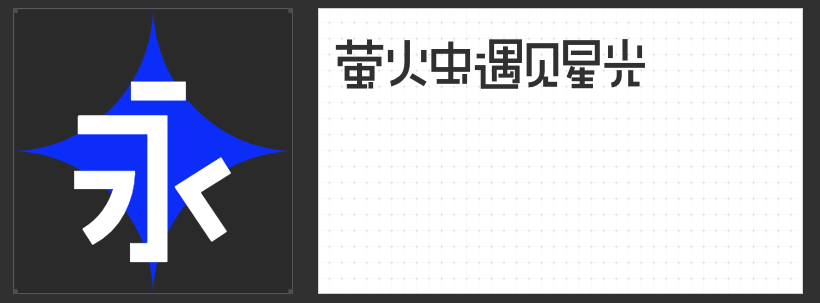
萌系设计字体推荐:用灵动字型唤醒治愈美学
在萌系设计中,字体的选择往往决定了整体氛围的基调——柔和的弧线、灵动的结构、恰到好处的“不完美”,都能让文字成为传递温暖与趣味的视觉符号。以下四款字体以独特的设计语言,为萌系创作注入鲜活的生命力。
一、励字敲可爱简 中粗
这款字体以手写圆润线条为基底,通过省略部分笔画与简化结构,打造出“用心书写却略带随性”的视觉效果。中粗的笔画粗细平衡了辨识度与轻盈感,避免因过于纤细而失去存在感,也未因过粗而显得笨拙。其独特之处在于保留手写痕迹的同时,融入几何化的处理——例如“口”字常被简化为圆角矩形,转折处带有自然的弧度,仿佛孩童信手涂鸦。这种“不完美的精致”让文字自带故事感,适合需要传递温暖、治愈氛围的场景。
二、字恋狂澄空 迟风
以“上松下紧”的重心布局为特点,这款字体通过灵活的字面结构与错落有致的笔画安排,营造出动态的视觉韵律。部分偏旁部首的占比差异(如左窄右宽或上小下大)打破常规平衡,却因整体协调的设计显得自然有趣。笔画处理上,流畅的弧线与利落的直线交织,折笔处采用平直切角减少锐度,搭配“断开”的笔画连接方式,让文字如音符般轻盈跳跃。这种设计既保留了手写的自然感,又通过结构变化赋予文字“呼吸感”。
三、字恋狂灵怪简
若说前两款字体是“温柔的萌”,这款则以“鬼马精灵”的气质脱颖而出。笔画连带处如行云流水,折笔处被刻意设计为三角形、圆形等几何图形,形成强烈的视觉记忆点。连笔的贯穿不仅提升了书写流畅感,更让文字仿佛拥有生命,在纸上自由舞动。这种打破常规的设计语言,适合需要突出个性、传递奇思妙想的萌系创作。
四、励字圆梦简 中黑
以圆润柔和为外衣,这款字体通过“外圆内方”的结构传递内在力量。直线笔画与竖折设计替代了传统弧线,简洁中透着利落;起笔、收笔与转折处的圆弧处理,则弱化了直线的生硬感。中宫松散的设计让文字如棉花糖般蓬松可爱,却因内方骨架而保持了结构稳定性。这种“柔软与坚韧并存”的特质,让文字既能营造温馨氛围,又不失专业感。
萌系设计的核心在于“情感共鸣”,而这四款字体通过手写温度、动态结构、几何创意与刚柔并济的设计语言,为文字赋予了超越符号的治愈力量。无论是需要传递温暖、表达个性,还是平衡可爱与专业,它们都能成为设计师手中不可或缺的“萌力工具”。